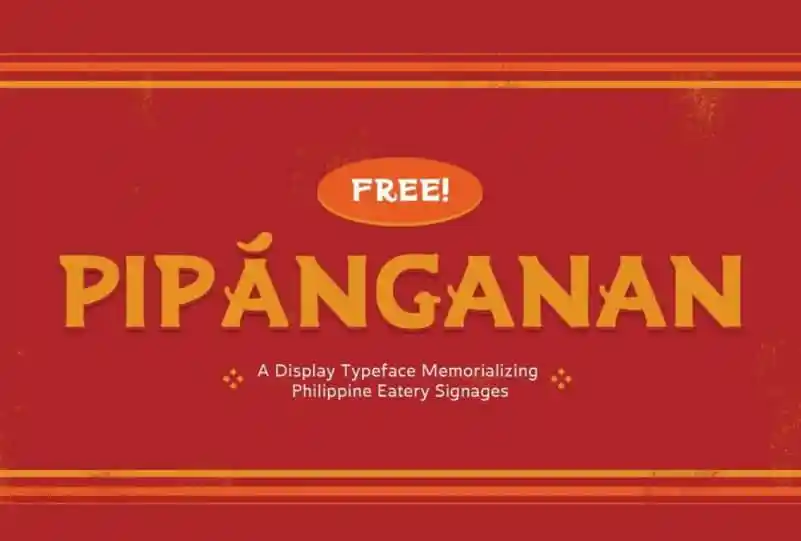
Pipánganan Display Font – Fonte Grátis
Pipánganan Display Font
A Pipánganan Display Font é uma tipografia de exibição que reúne elementos de serifas arredondadas, representando clareza, contraste e agudeza. Ela foi criada pelo designer Cid Gonzales, inspirado nas sinalizadoras de restaurantes carinderias e outras lojas da região local filipina. Esta fonte está disponível gratuitamente e é ideal para usar em aplicativos digitais que desejam se destacar com um estilo gráfico distintivo e moderno. Seja em anúncios, logotipos ou qualquer outro tipo de design digital, Pipánganan traz uma atmosfera vibrante e orgânica, perfeita para criar marcas visuais atraentes que se encaixam perfeitamente com o espírito do Brasil.